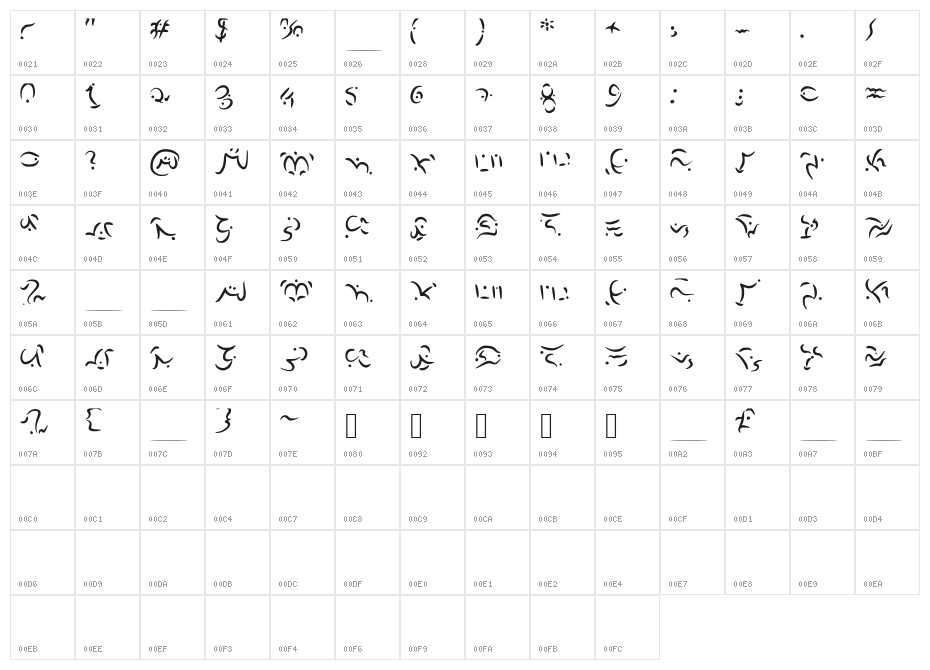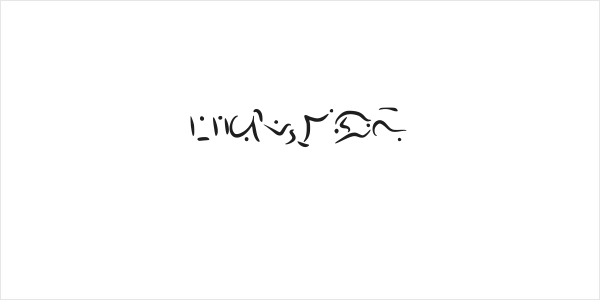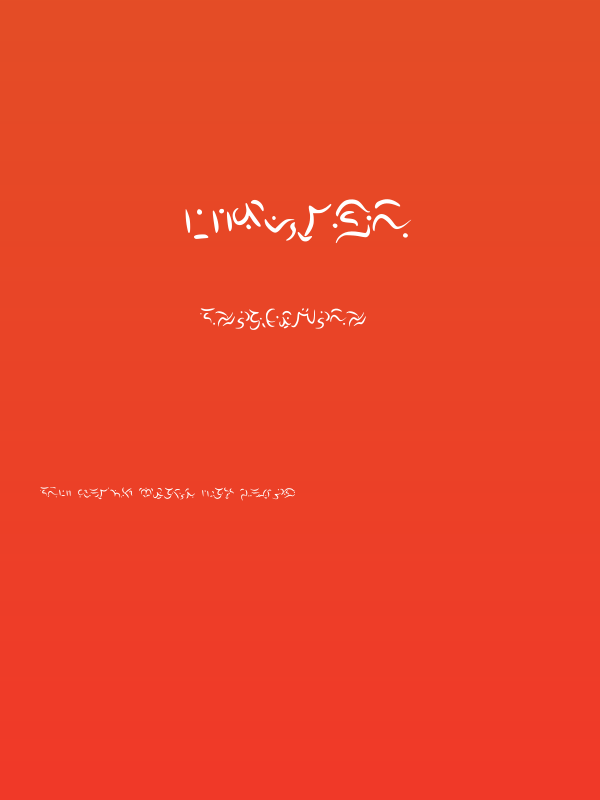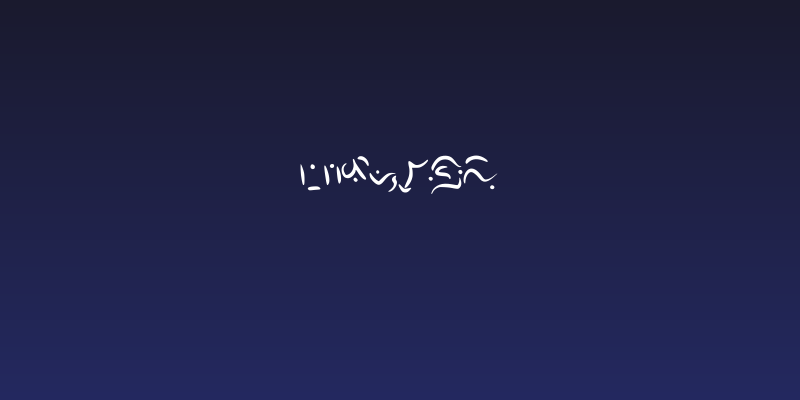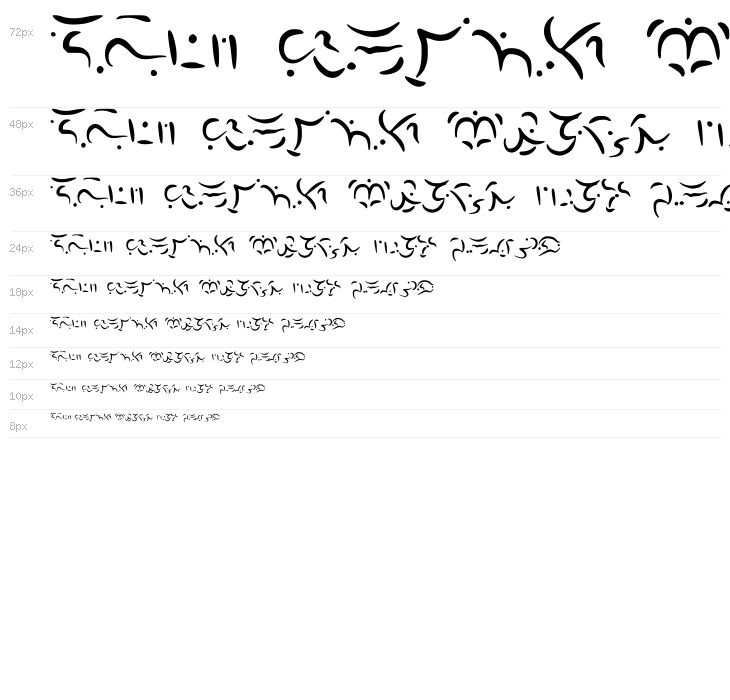
Elvish Font
| Caso d'uso | Logos, Titles, Decorative elements |
| Progetti proposti | Ideal for fantasy-themed projects, book covers, movie titles, or any creative work that requires a touch of elegance and mystique. |